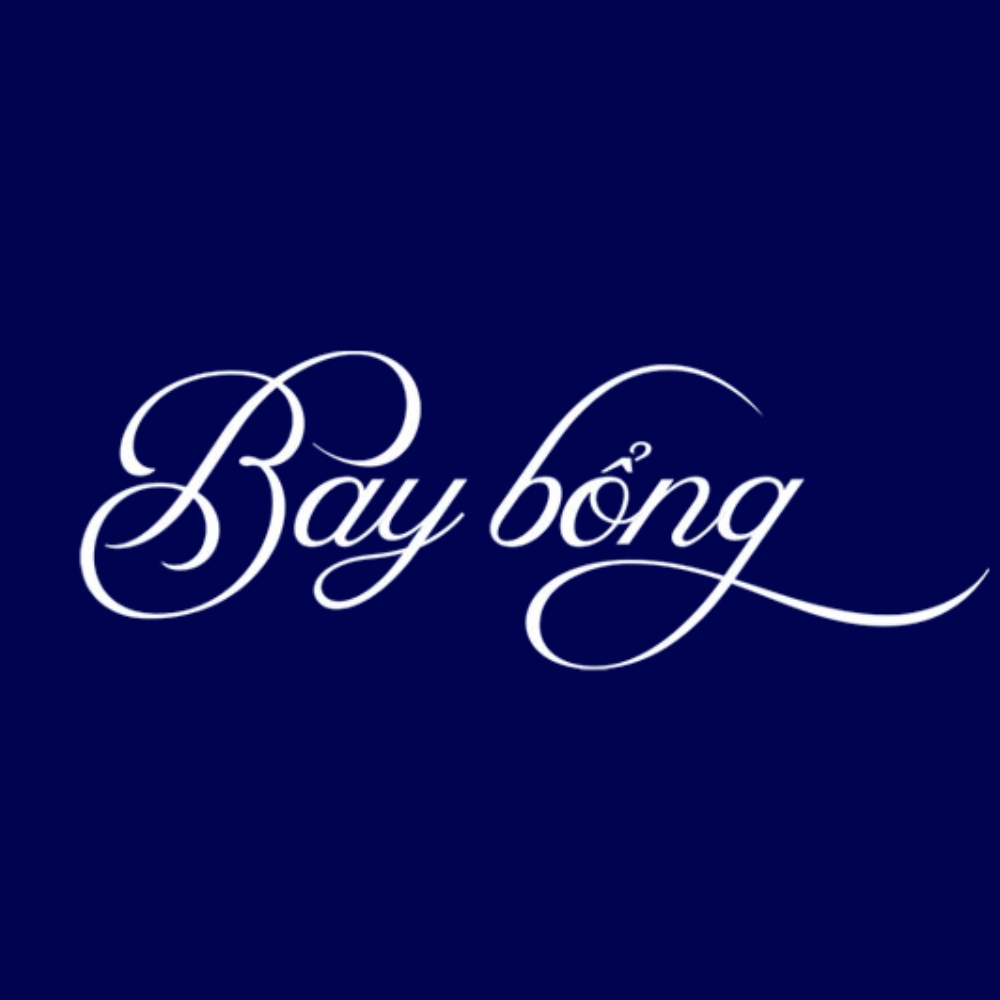
Trong các bản phối cảnh kiến trúc hay bộ nhận diện thương hiệu cho không gian nghỉ dưỡng, những đường nét mềm mại của font chữ bay bổng luôn mang đến sức sống và cảm hứng sáng tạo mạnh mẽ. Khác với những kiểu chữ in ấn truyền thống khô cứng, dòng font này mô phỏng nhịp điệu của các nét bút tay, giúp cân bằng lại các hình khối vuông vức của những công trình xây dựng.
Sức hút thẩm mỹ của các dòng font chữ bay bổng trong trang trí
Điểm lôi cuốn của phông chữ bay bổng chính là sự biến thiên linh hoạt giữa các nét thanh và nét đậm, tạo nên một dòng chảy văn bản tự nhiên và lôi cuốn. Khi ứng dụng vào thực tế, các bộ font này giúp tiêu đề trở nên có hồn hơn, gợi mở cảm giác về sự thư thái, lãng mạn và tự do. Phiên bản Việt hóa chuẩn Unicode giúp người dùng trình bày nội dung tiếng Việt ổn định, tránh các lỗi nhảy dấu hay sai ký tự thường gặp, duy trì tính thẩm mỹ đồng nhất cho toàn bộ sản phẩm thiết kế.
Sự tinh tế của font bay bổng còn nằm ở khả năng tạo ra điểm nhấn thị giác ngay lập tức. Những đường uốn lượn được xử lý kỹ lưỡng mang lại vẻ đẹp chuyên nghiệp, phù hợp để thể hiện cá tính riêng của thương hiệu hoặc cá nhân kiến tạo. Đây là phương án hiệu quả để nâng tầm giá trị cho các bản thuyết minh dự án, giúp khách hàng dễ dàng cảm nhận được sự tâm huyết và tư duy thẩm mỹ của đơn vị tư vấn thiết kế.
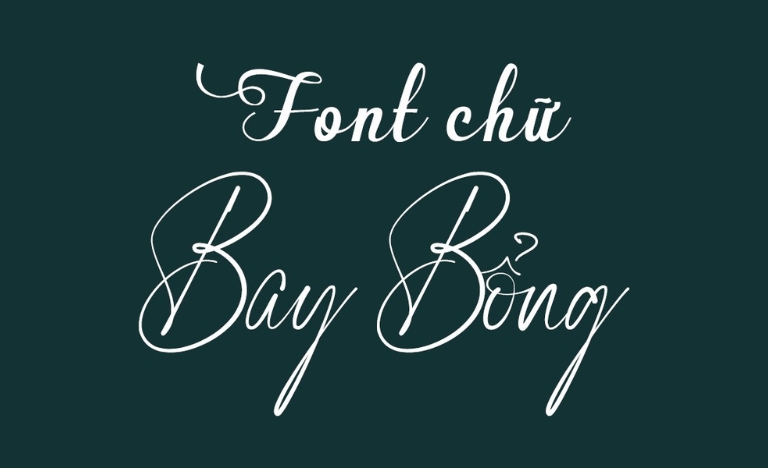
| Phân loại phong cách | Script / Calligraphy / Handwriting |
| Bảng mã hỗ trợ | Unicode Việt Nam chuẩn |
| Đặc tính hiển thị | Nét thanh đậm, uốn lượn mềm mại |
| Lĩnh vực phù hợp | Logo homestay, Poster, Thiệp mời, Decor |
Gợi ý lựa chọn: Khi sử dụng phông chữ bay bổng, bạn nên đặt chúng trên những nền màu tối giản hoặc hình ảnh có chiều sâu để tôn vinh sự tinh tế của nét chữ. Việc phối hợp cùng một font không chân mảnh sẽ giúp tổng thể thiết kế trở nên chuyên nghiệp và hiện đại hơn.
03 Ứng dụng đưa font bay bổng vào thực tế không gian sống
Nhờ vẻ ngoài giàu tính nghệ thuật và sự thanh lịch, bộ font chữ này mang lại giá trị thực tế cao khi được đưa vào các hạng mục quảng bá và trang trí công trình hiện đại:
- Bảng nhận diện cho Homestay & Boutique Hotel: Những nét chữ uốn lượn rất ăn ý khi xuất hiện trên chất liệu mica gương hoặc khắc laser trên gỗ tại các khu nhà lắp ghép nghỉ dưỡng. Điều này giúp không gian toát lên vẻ chuyên nghiệp và thu hút du khách yêu thích cái đẹp.
- Thiết kế bộ quà tặng doanh nghiệp: Sử dụng font nghệ thuật cho tên thương hiệu trên các vật phẩm như bình giữ nhiệt, sổ tay giúp tăng giá trị tinh thần và thể hiện sự tỉ mỉ của người tặng đối với đối tác, khách hàng.
- Trang trí không gian nội thất Zen: Bạn có thể dùng font này để làm tranh quotes trang trí hoặc cắt chữ nổi đèn neon tại phòng khách, khu vực sảnh chờ nhằm tạo điểm nhấn đầy lôi cuốn cho không gian sống hiện đại.
03 Lưu ý khi trình bày bố cục với phông chữ bay bổng để đạt hiệu quả cao
Để khai thác hiệu quả vẻ đẹp của dòng font đặc thù này mà không làm rối mắt người xem, người thiết kế nên lưu tâm một số kinh nghiệm sau:
- Kiểm soát khả năng đọc hiểu: Do nét chữ có nhiều chi tiết uốn lượn, bạn nên ưu tiên sử dụng cho các tiêu đề ngắn hoặc slogan. Tránh dùng cho các đoạn văn bản dài vì sẽ gây mỏi mắt và làm mất đi trọng tâm thẩm mỹ của bản thiết kế.
- Nới rộng khoảng cách dòng: Hãy đảm bảo khoảng cách giữa các dòng đủ thoáng để các nét móc và dấu tiếng Việt không bị chồng lấn lên nhau, giúp văn bản giữ được sự minh bạch khi nhìn từ xa.
- Hạn chế viết hoa toàn bộ: Đặc trưng của font script là sự liên kết nhịp nhàng giữa các chữ thường. Việc viết hoa toàn bộ cụm từ sẽ làm mất đi tính nhịp điệu tự nhiên và làm cho tiêu đề trở nên thô cứng, thiếu thẩm mỹ.